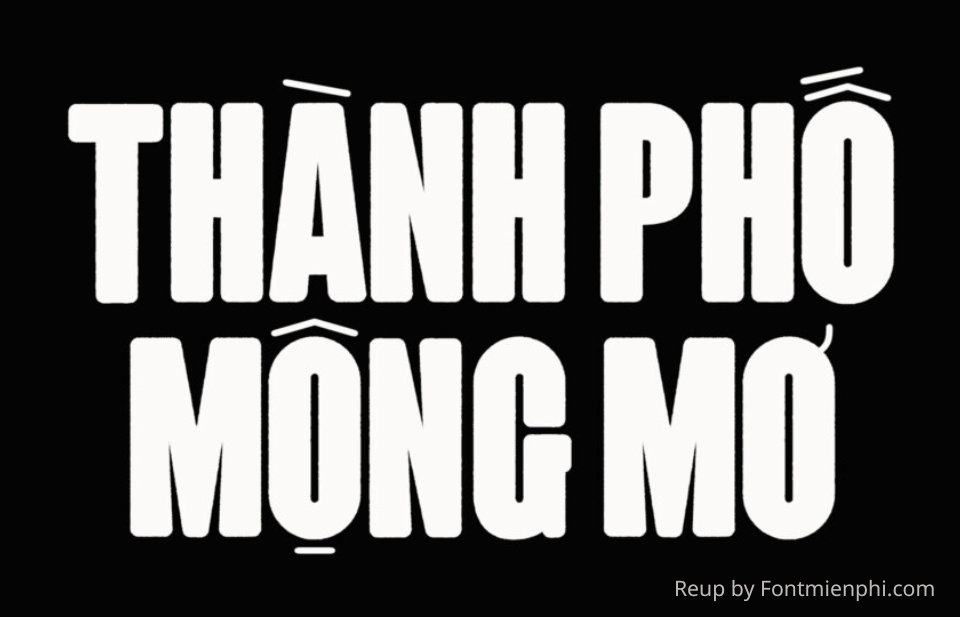
Font PS Bolden Việt Hóa là một phông chữ hiển thị (Display Font) mang phong cách dày dặn, mạnh mẽ và cực kỳ nổi bật. Được thiết kế tối ưu với các đường nét cứng cáp nhưng không kém phần hiện đại, bộ font này đã được việt hóa hoàn chỉnh, chỉnh chu từng dấu câu, giúp các nhà thiết kế dễ dàng tạo ra những điểm nhấn thị giác ấn tượng trên mọi ấn phẩm.
Đặc điểm nổi bật của PS Bolden
• Trọng lượng chữ (Weight) ấn tượng: Đúng như tên gọi “Bolden”, font chữ sở hữu độ dày dặn và “nặng” đặc trưng. Cấu trúc chữ chặt chẽ giúp nó chiếm lĩnh không gian rất tốt, tạo cảm giác quyền lực và vững chãi.
• Việt hóa chuẩn xác: Toàn bộ bảng mã tiếng Việt (bao gồm các bộ dấu khó như ề, ễ, ợ, ử…) đều được kern (chỉnh khoảng cách) và thiết kế lại tỉ mỉ. Dấu chữ hòa hợp hoàn toàn với nét gốc, đảm bảo không bị gãy hay lệch form khi gõ văn bản dài.
• Dễ đọc ở kích thước lớn: Dù rất dày, các khoảng âm (counter) bên trong từng chữ cái vẫn được xử lý khéo léo để đảm bảo tính dễ đọc (legibility) khi hiển thị ở kích thước lớn.
Ứng dụng thực tế trong thiết kế
Với đặc tính thu hút sự chú ý mạnh mẽ, PS Bolden là “vũ khí” đắc lực cho các hạng mục thiết kế cần sự nổi bật:
• Thiết kế Thumbnail YouTube & Video Cover: Cực kỳ phù hợp để làm text chính (Big Typography) trên các thumbnail, giúp video thu hút ánh nhìn ngay lập tức nhờ nét chữ to, rõ và ấn tượng khi đặt ở góc phải hoặc trung tâm khung hình.
• Thiết kế Logo & Bộ nhận diện thương hiệu: Mang lại cảm giác trẻ trung, hiện đại và khỏe khoắn cho các thương hiệu về thời trang đường phố (streetwear), thể thao, công nghệ hoặc F&B.
• Poster, Standee & Banner quảng cáo: Tuyệt vời khi dùng làm tiêu đề (Headline) cho các chương trình khuyến mãi, sự kiện âm nhạc hay các chiến dịch marketing cần sự bùng nổ.
• In ấn bao bì (Packaging): Tạo điểm nhấn cực mạnh trên vỏ hộp, nhãn mác sản phẩm.